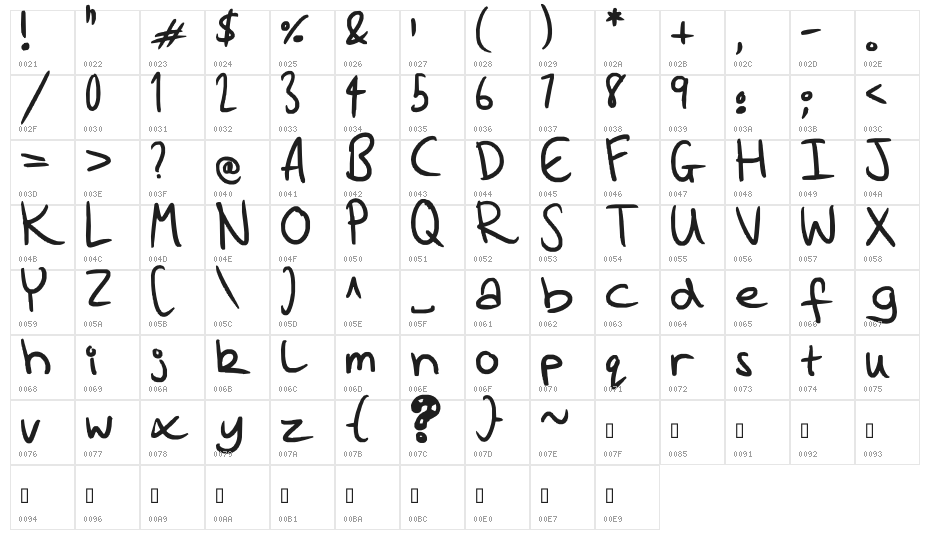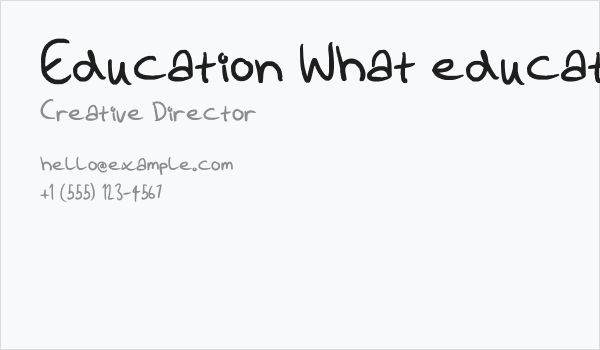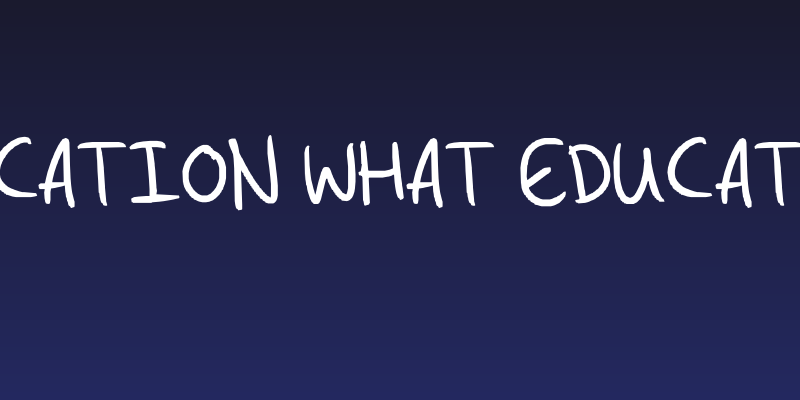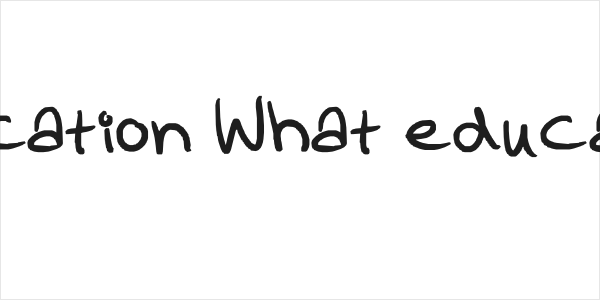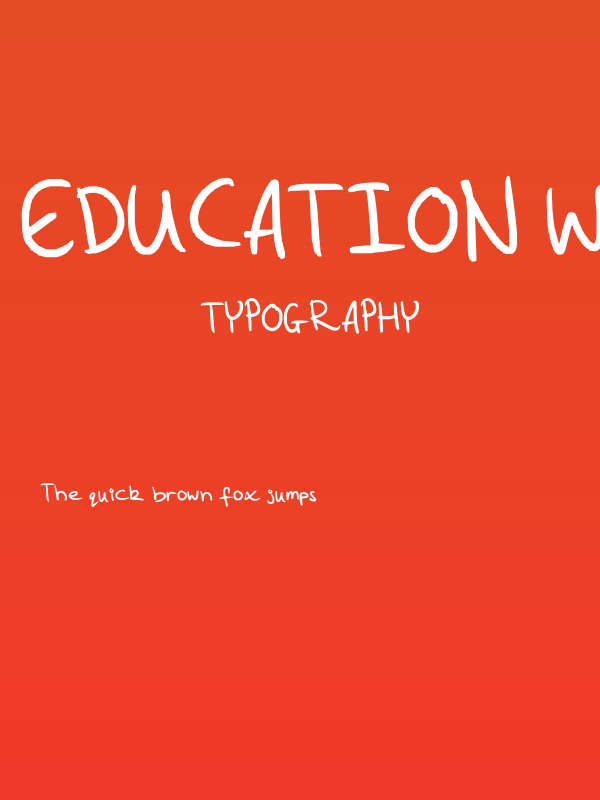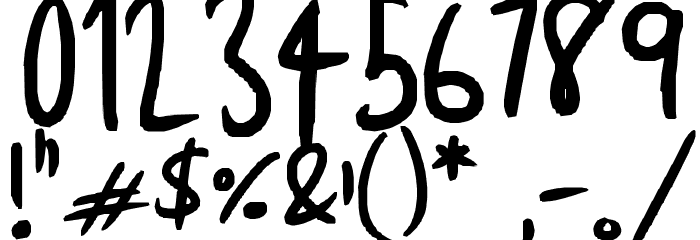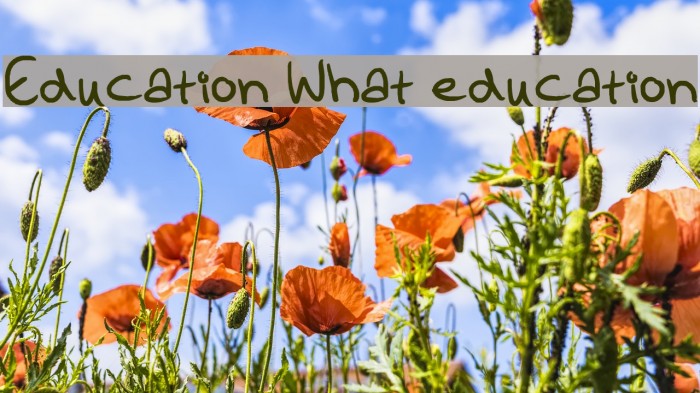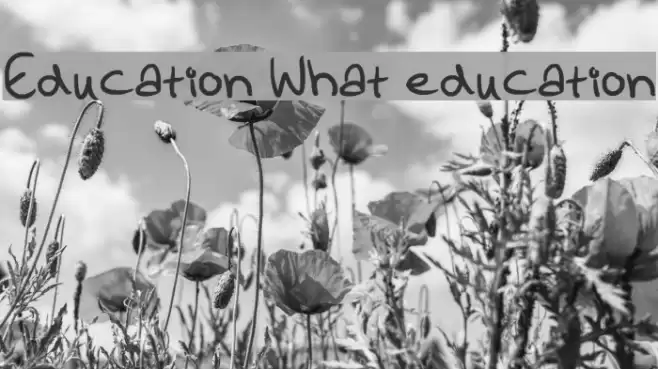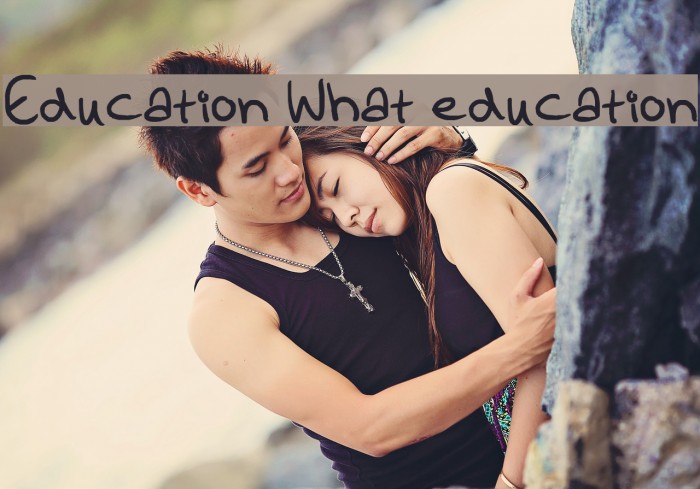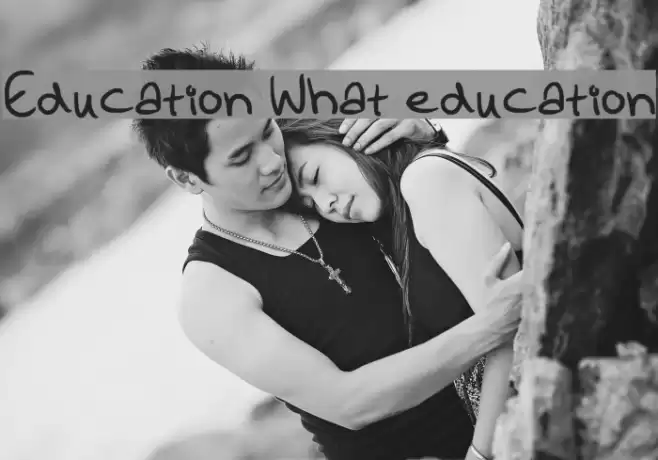
Education What education Font
| Style général | Casual |
| Cas d'utilisation | Headlines, Informal text, Creative projects |
| Projets proposés | Ideal for greeting cards, children's books, casual branding, and social media graphics. |